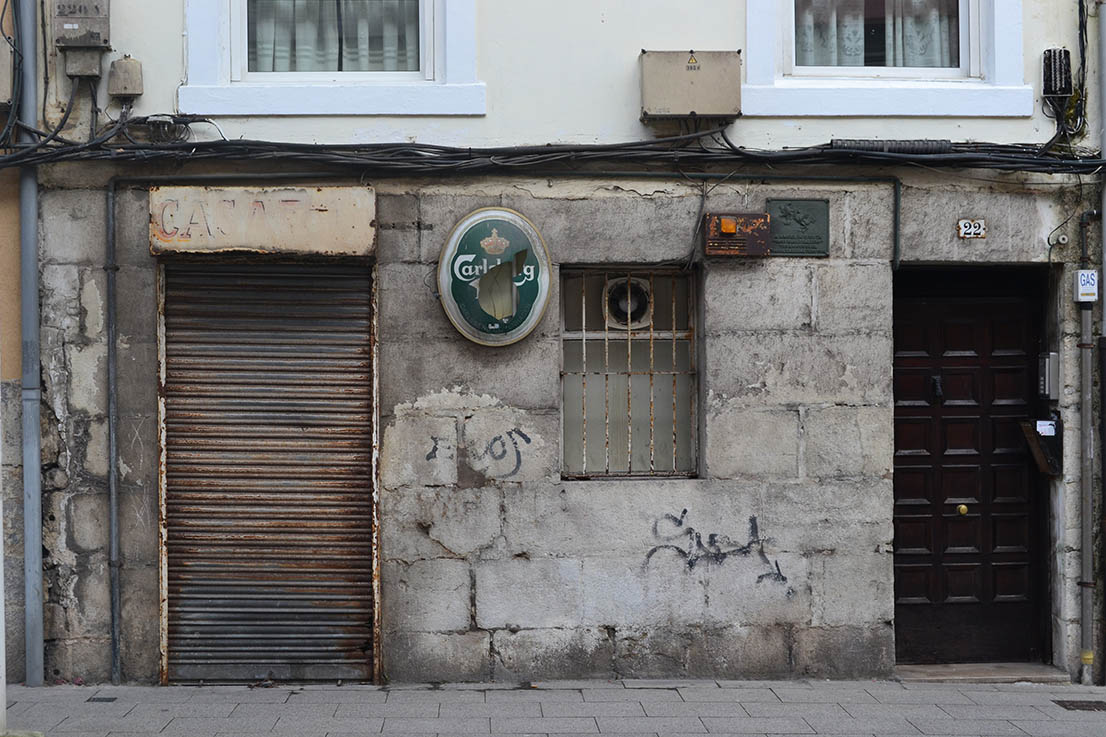
Sorpresa en Casa Sota
En un paseo por la Calle Alta, cuando estaba pasando junto a Casa Sota descubrí que se había retirado un cartel anunciador de una marca de cerveza y una placa conmemorativa de los vecinos hacia Ángel C. Sota, con una imagen de las peleas de gallos que allí realizaban. Como hemos dicho, en ese local comenzó lo que posteriormente se conocería como Quiniela.
La sorpresa es que debajo del cartel ha aparecido un dibujo de un plato y encima una serie de letras rotuladas. Por lo que nos da idea que en la fachada había anuncios en relación a lo que en el bar se podía consumir, especialmente sus conocidlos Callos. Debajo del negativo de la forma se intuye también un texto: «Mesa y (mantel)»